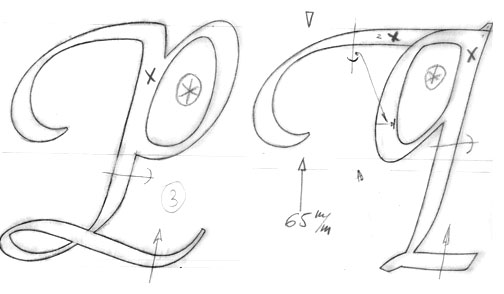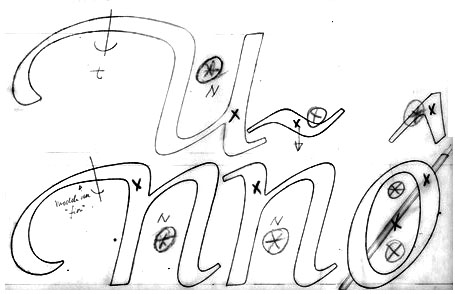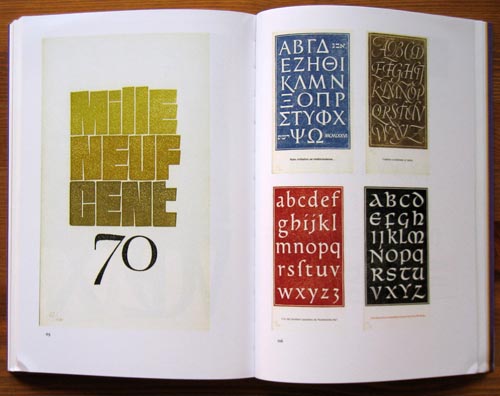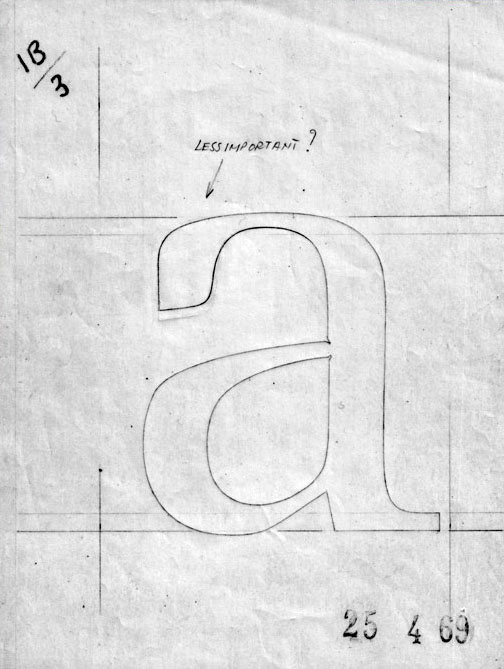
José Mendoza y Almeida (*1926)A contribuição francesa para os últimos 100 anos da Tipografia tem sido magra. Sem dúvida que há contribuições importantes, nomeadamente de Georges Peignot, A.M. Cassandre, Marcel Jacno, François Ganeau, Roger Excoffon, Ladislas Mandel, Thierry Puyfoulhoux, Franck Jalleau, Jean François Porchez, Maximilien Vox, Jean-Baptiste Levée, Mathieu Réguer e Jonathan Perez.José Mendonza y Almeida, um dos menos conhecidos e menos citados, poderá ser um dos mais importantes...
ITC Mendoza. Based on characters of Aldus Manutius. He recreates the vigour of the first humanes and garaldes well. José de Mendoza y Almeida, 1992, itc. From 1985 to 1990 he taught type design at the Imprimerie Nationale, Paris, where his students included Thierry Puyfoulhoux, Frank Jalleau, and Poul Sogren. O typeface designer francês mais idoso, ainda está em actividade. Nasceu em Sèvres (França) em 1926. José Mendoza y Almeida est le dessinateur de caractères français le plus ancien toujours en activité. Il possède la particularité davoir publié ses principales créations dans les plus grandes fonderies internationales. Sa longue carrière, ponctuée par de nombreux travaux de graphisme et de calligraphie? pour lédition, la publicité et la communication, la amené à travailler avec dimportantes figures telles que Maximilien Vox et Roger Excoffon. Il enseigna également à lAtelier national de création typographique au sein de lImprimerie nationale. Cet ouvrage, le premier qui soit dédié à son uvre, est composé dune introduction de Jan Middendorp et de plusieurs essais écrits par Martin Majoor et Sébastien Morlighem, consacrés au Pascal, au Photina, à lITC Mendoza Roman et à dautres créations moins connues. De nombreux documents inédits sont reproduits pour la première fois. José Mendoza y Almeida was perhaps the most internationally active 20th century French type designer. While he also produced work for local distributors, his most significant faces were published by companies abroad, including the Amsterdam Typefoundry, Monotype, and ITC. Born in 1926, Mendozas career has been primarily devoted to activities in the fields of graphic design, illustration, and calligraphy. During his professional career, he has never worked as a full-time type designer, although he was a typographic educator from 19851990. His Pascal, Photina, and ITC Mendoza Roman typefaces are currently on the market, and each has played its own significant role in the history of 20th century type. He began working with Roger Excoffon at the Fonderie Olive in 1954, and is still active today. Many consider him to be the godfather of French type design. The first book dedicated to his work was published last March as part of the Bibliothèque typographique series. It features an introduction by Jan Middendorp and essays by Martin Majoor and Sébastien Morlighem. The book also contains many previously unpublished documents